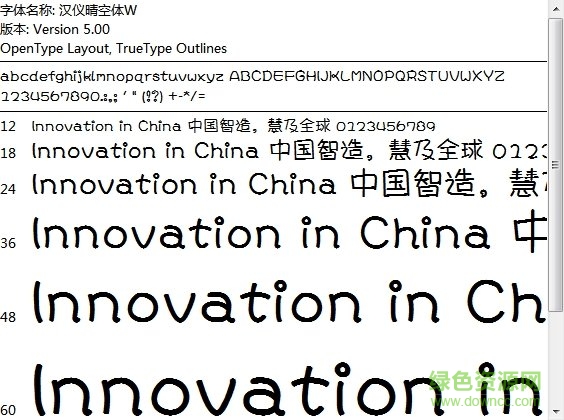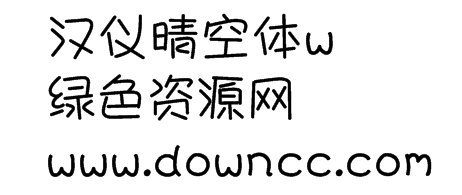
漢儀晴空體w regular
漢儀晴空體w是在漢儀晴空體的基礎(chǔ)上的完善版本,字庫(kù)更加完整,能滿足更多的設(shè)計(jì)需求,風(fēng)格模板上并未有大的改動(dòng),需要的朋友就來(lái)綠色資源網(wǎng)試試吧!
漢儀晴空體w regular介紹
漢儀晴空體簡(jiǎn)是一款具有手寫POP風(fēng)格的卡通字體,該字體俏皮可愛,趣味實(shí)足,非??ㄍā_m合應(yīng)用于廣告設(shè)計(jì)、名片設(shè)計(jì)、包裝印刷、產(chǎn)品設(shè)計(jì)等應(yīng)用。
漢儀晴空體是一款非常好看的藝術(shù)字體,常用于photoshop相關(guān)的平面設(shè)計(jì),在一般的瀏覽器、閱讀器、辦公軟件中,漢儀字庫(kù)特別為廣大文藝青年準(zhǔn)備了“年味”十足的古風(fēng)書法字體,把地道的中國(guó)風(fēng)帶給大家。